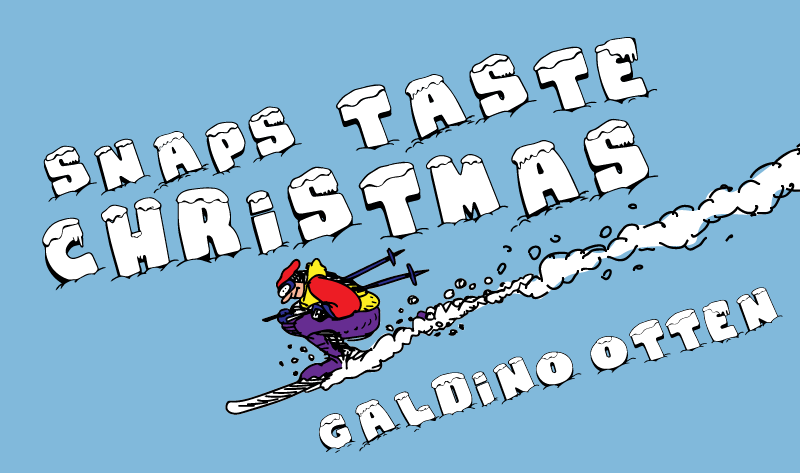
A fonte “Snaps Taste Christmas Font” é perfeita para personalizar uma sensacional experiência de Natal, mas esta não é sua única utilidade. Embora seja principalmente projetada para um formato horrível e macabro, suas linhas estilizadas ainda podem ser usadas em designs mais alegres e festivos, como cartões de aniversário ou cartazes de eventos natalinos. Se você está procurando por uma fonte que se destaca na categoria dos horror fonts, não pode deixar de experimentar “Snaps Taste Christmas Font”. Ideal para personalizar mensagens em seu próximo evento Halloween ou até mesmo para alguns designs macabros, a “Snaps” oferece uma mistura única e chocante entre o clássico e o grotesco. A fonte vem da designer certa – Hamilton, garantindo um toque de criatividade que torna qualquer projeto diferente. Download já!